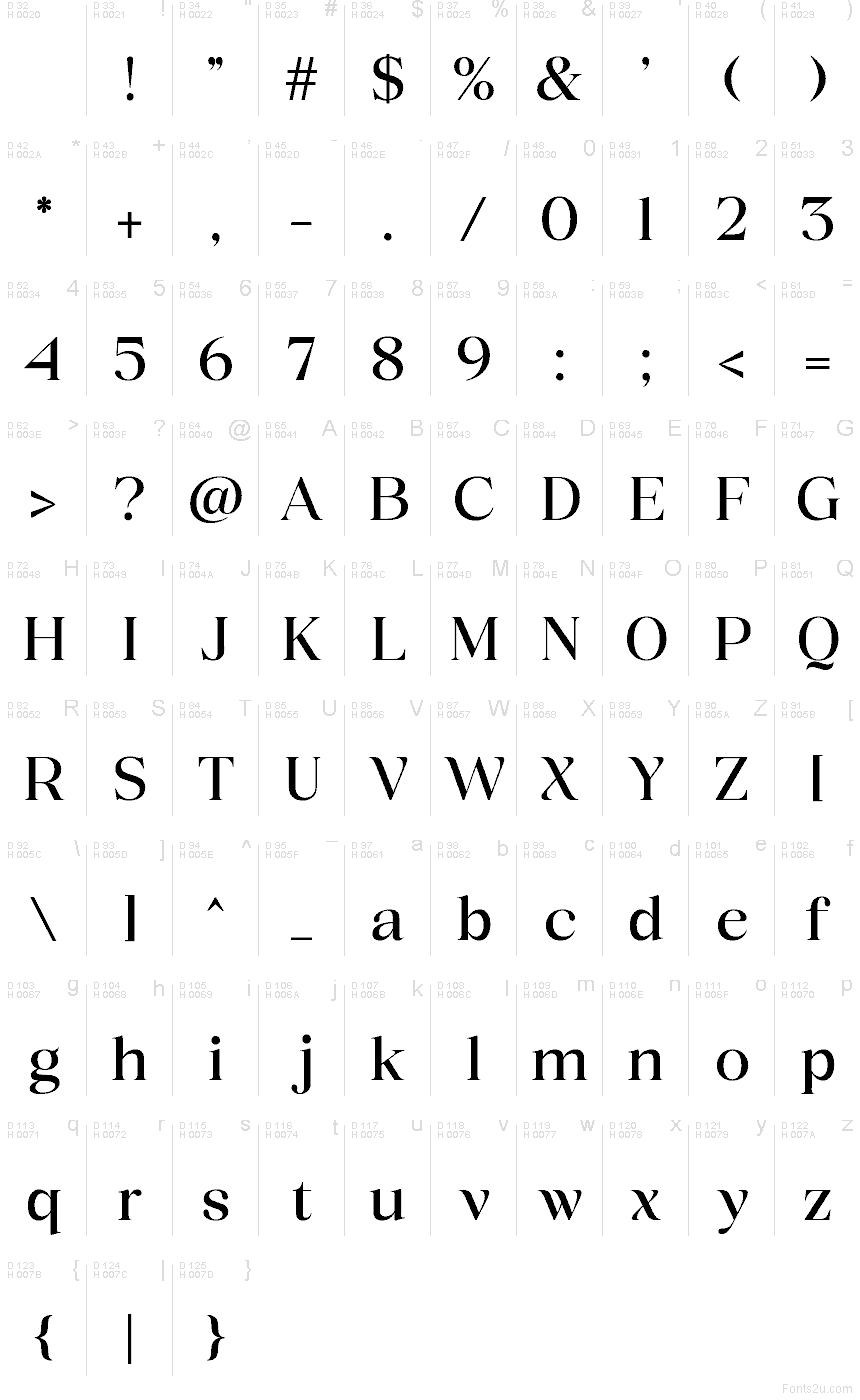
Scaver di Glyphminds Studios è un carattere serif gratuito ad alto contrasto con un tono editoriale e di tendenza. Le lettere combinano curve sinuose con giunzioni finissime e punte nette, conferendo al font un aspetto elegante e drammatico, tutt'altro che accademico o antiquato.
È ideale per testate di riviste, packaging di bellezza, copertine di libri, titoli di poster e marchi raffinati che richiedono quel tocco di classe in più. Come font gratuito, Scaver è particolarmente adatto per titoli brevi, richiami in copertina e monogrammi, poiché il marcato ritmo tra pieni e vuoti dona una presenza sofisticata anche alle combinazioni di lettere più semplici.